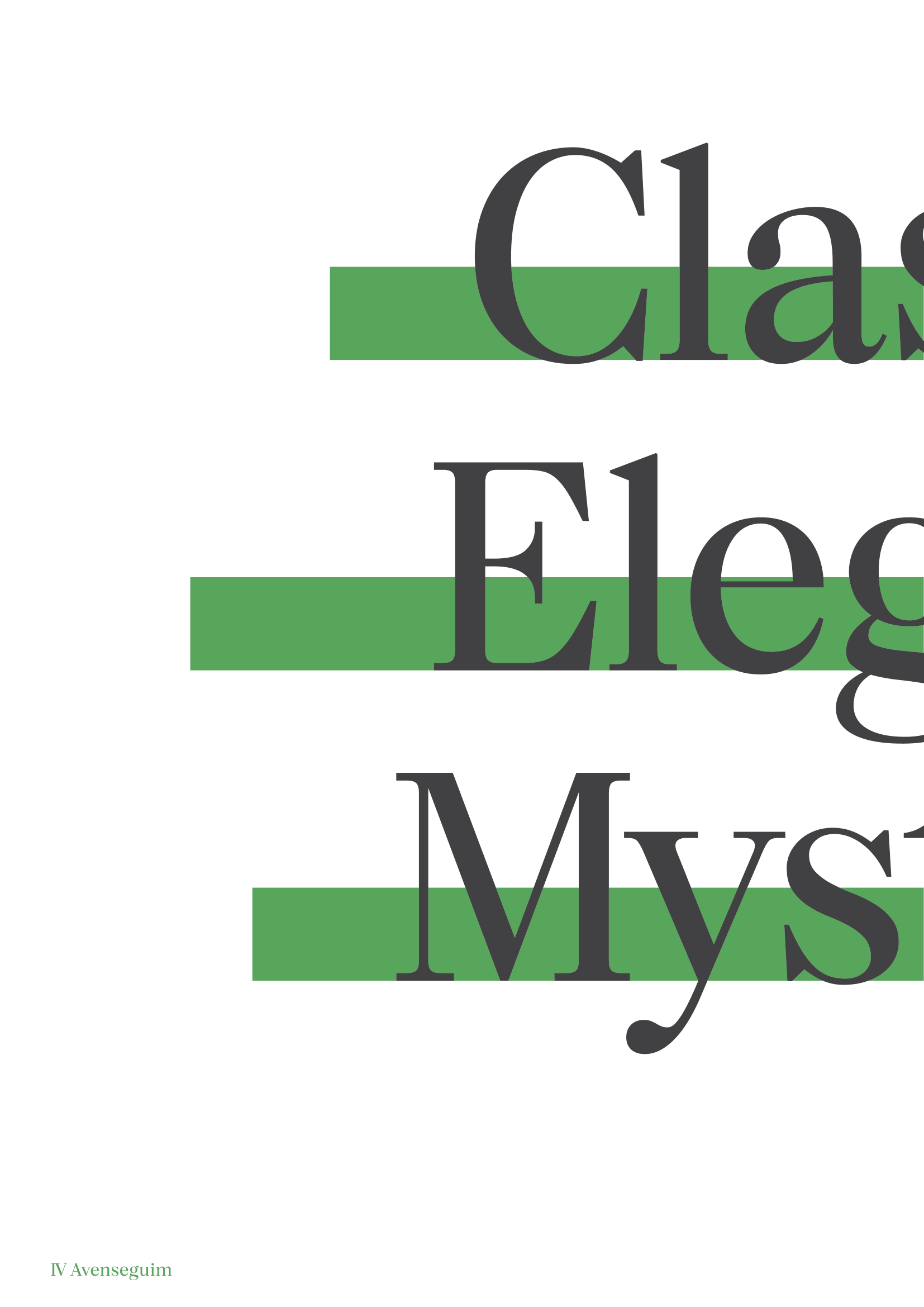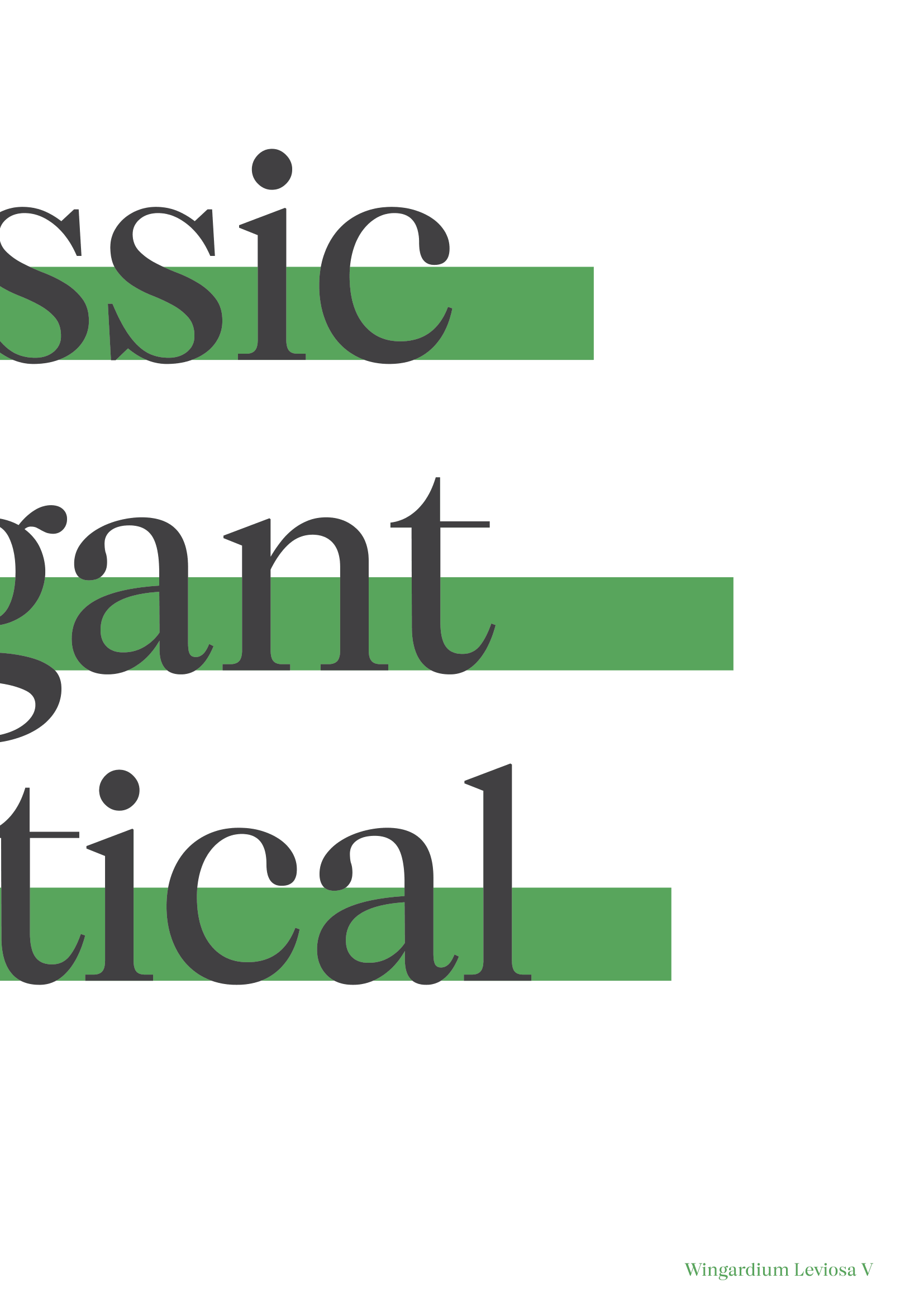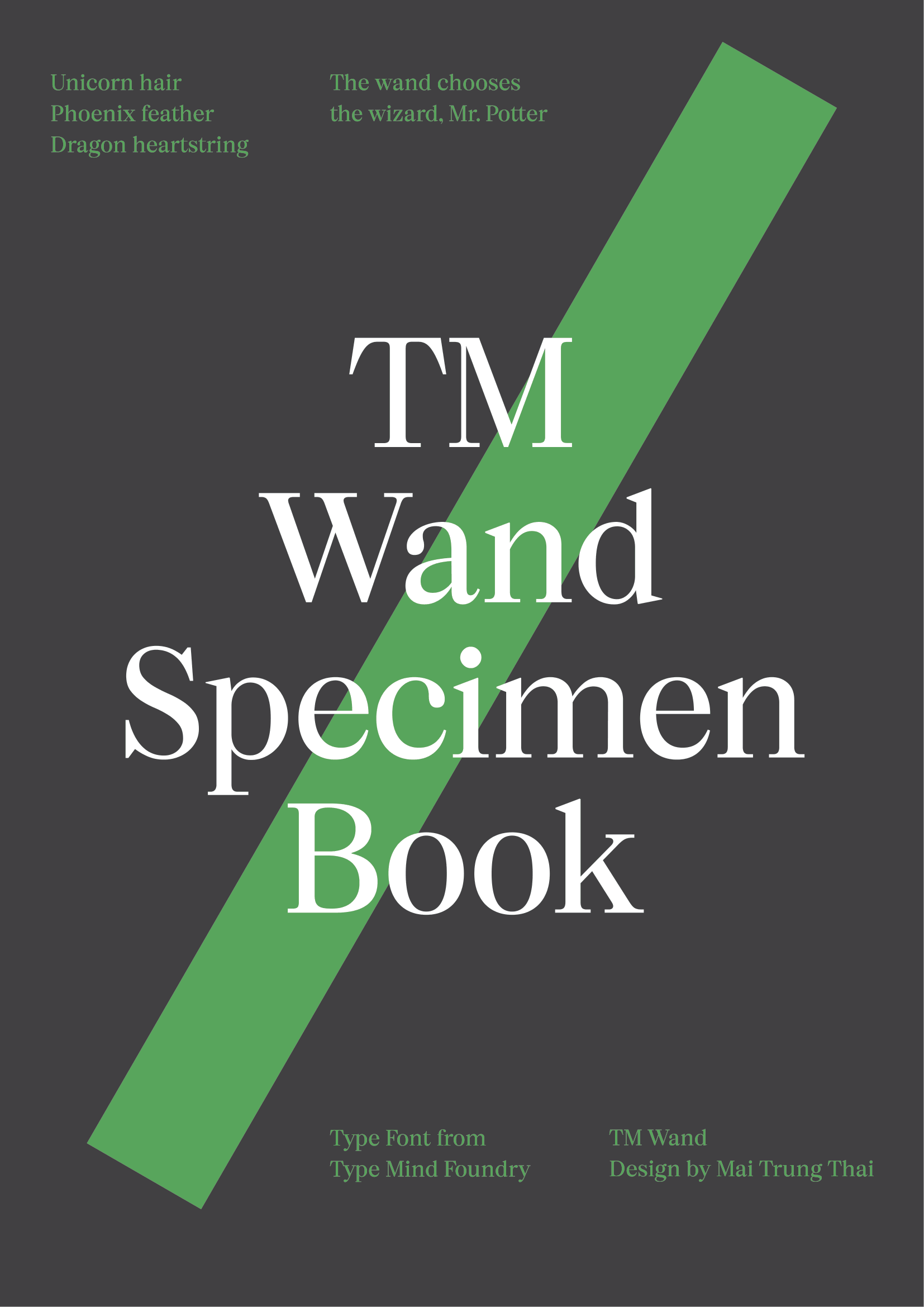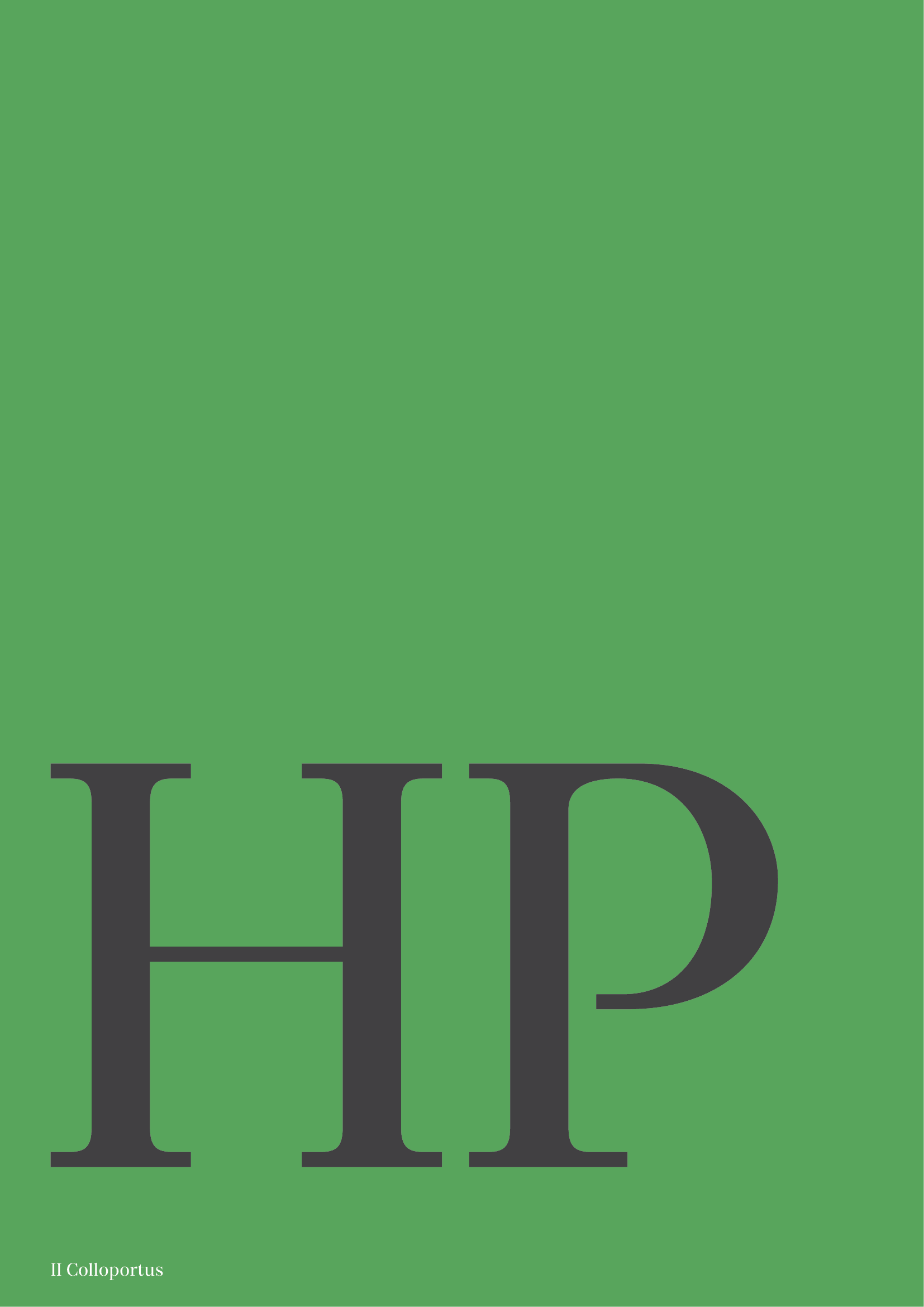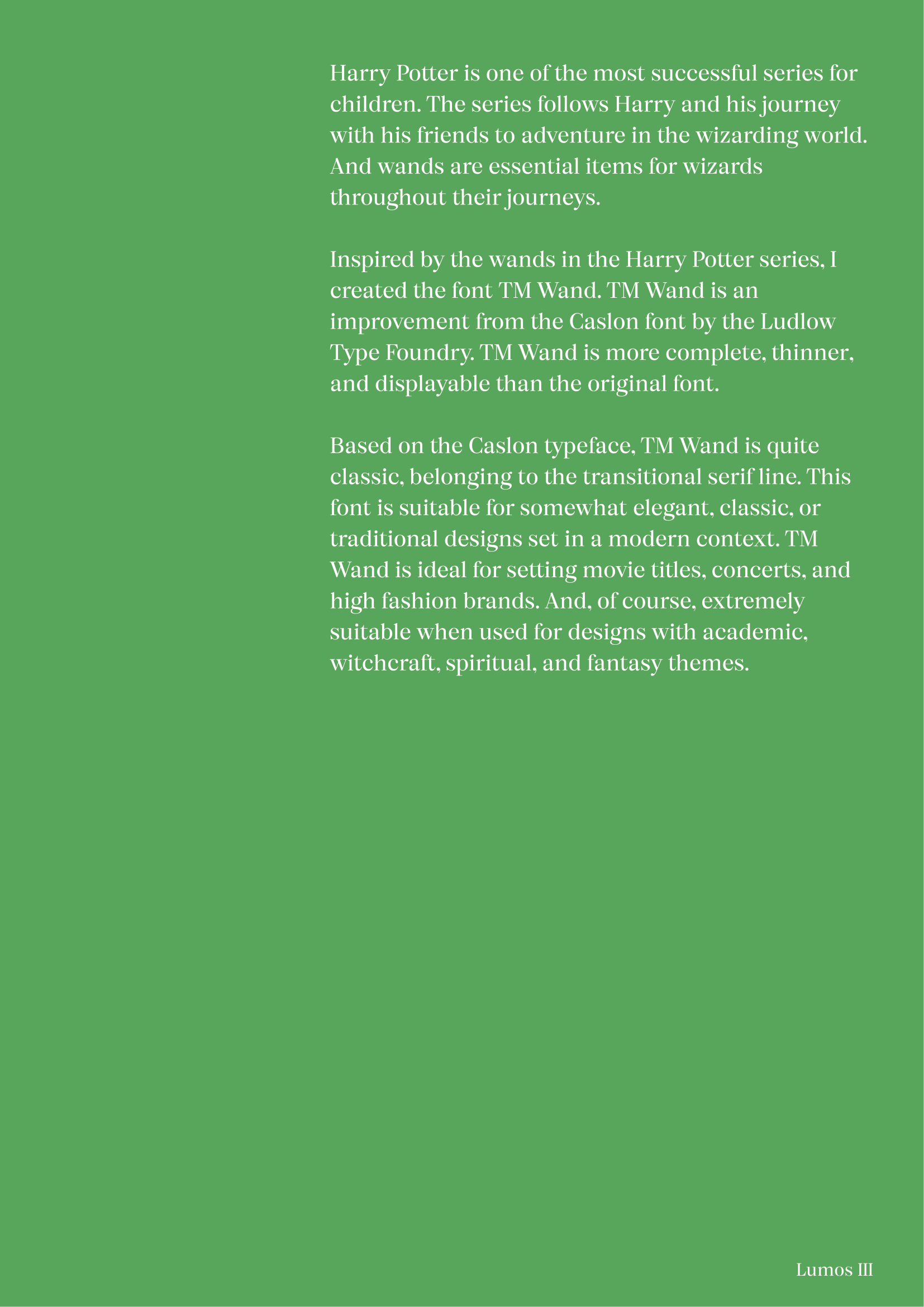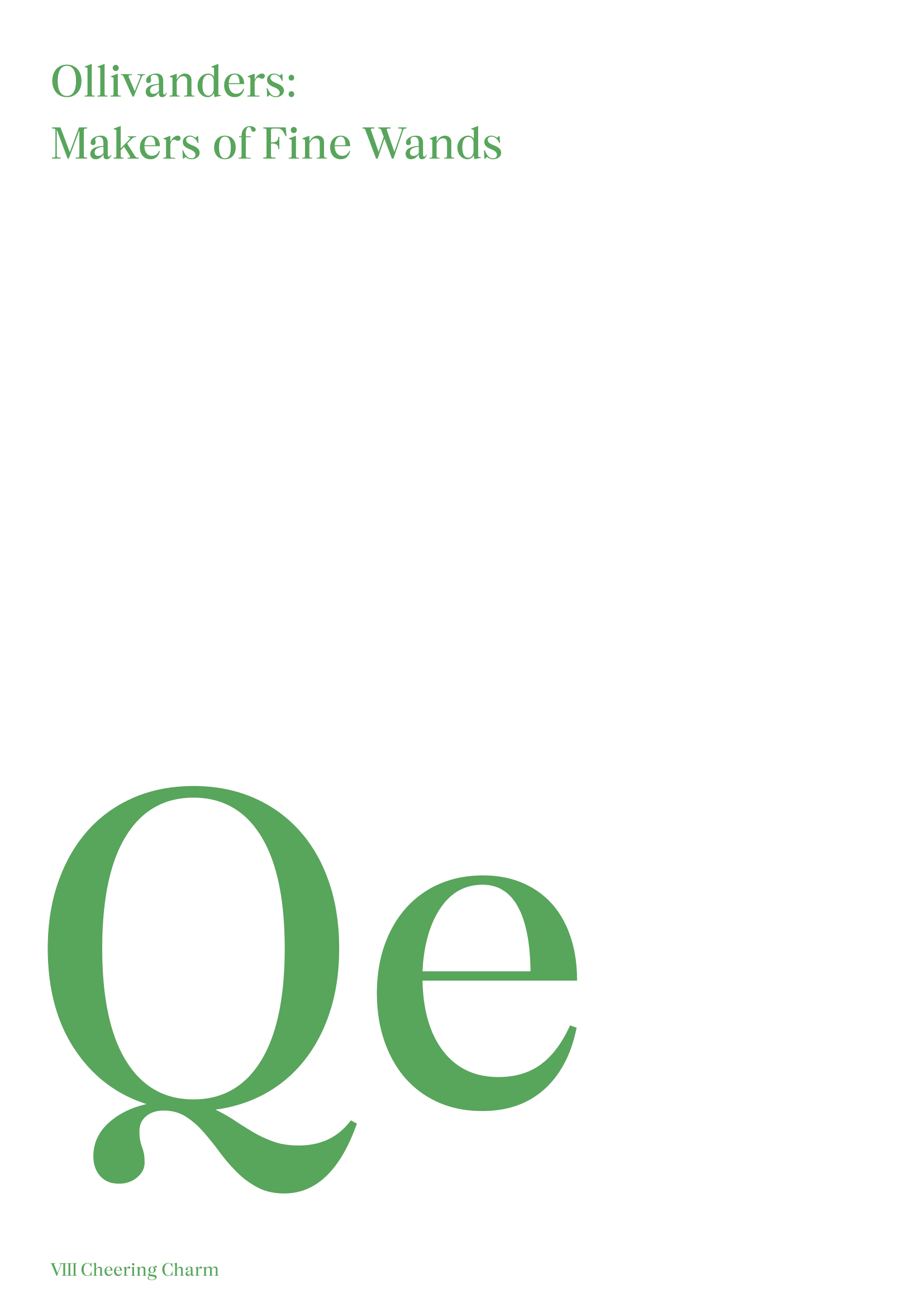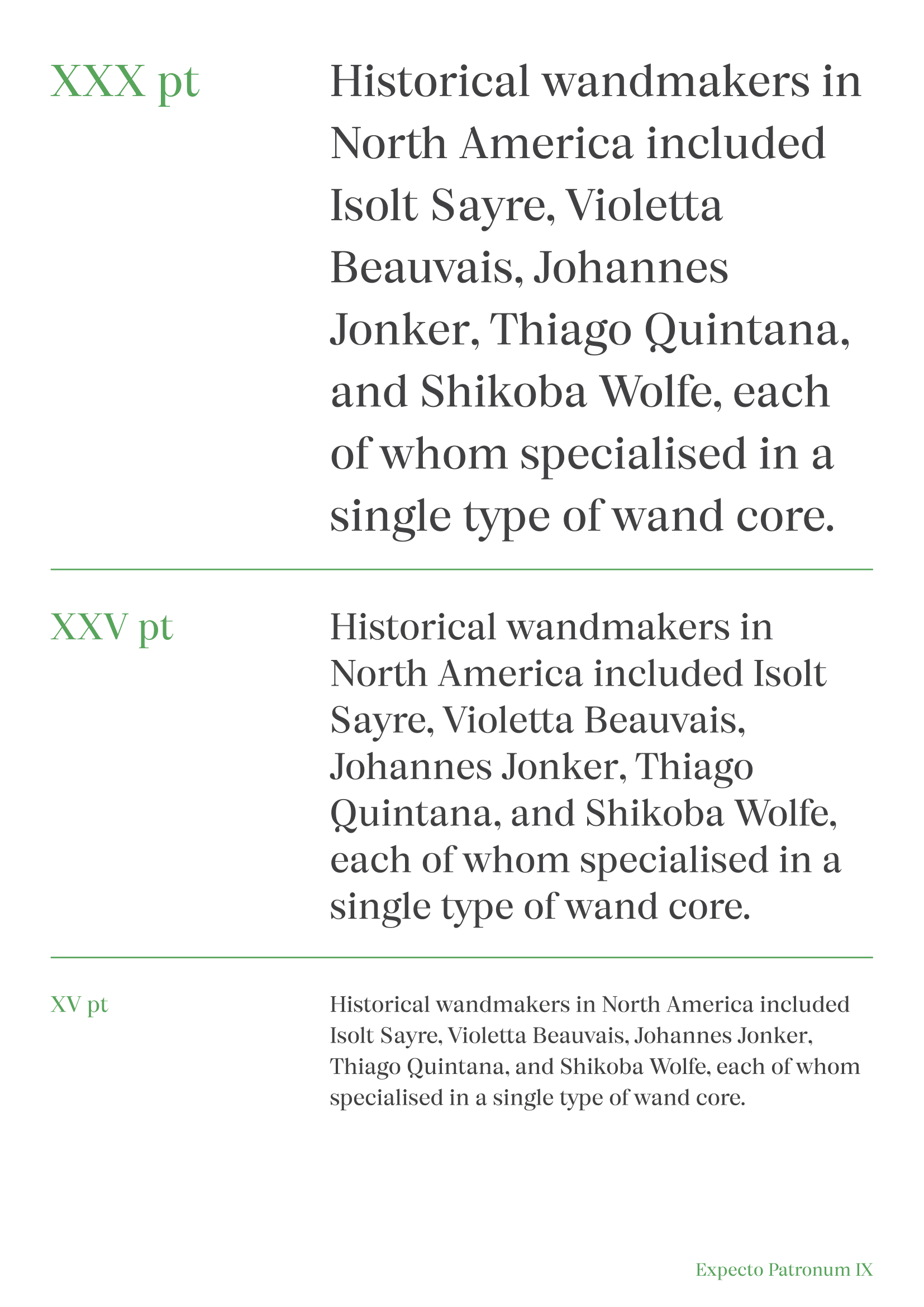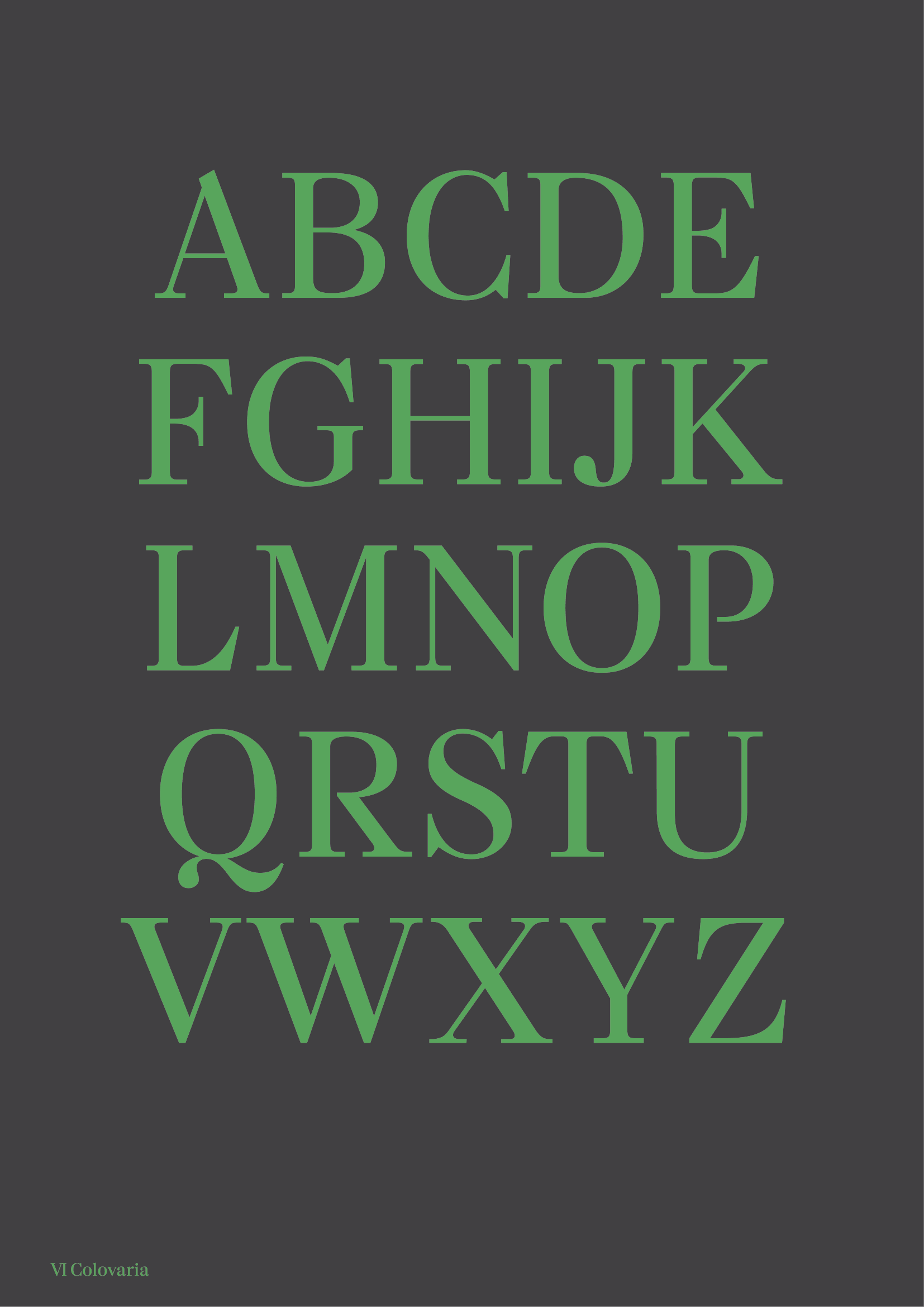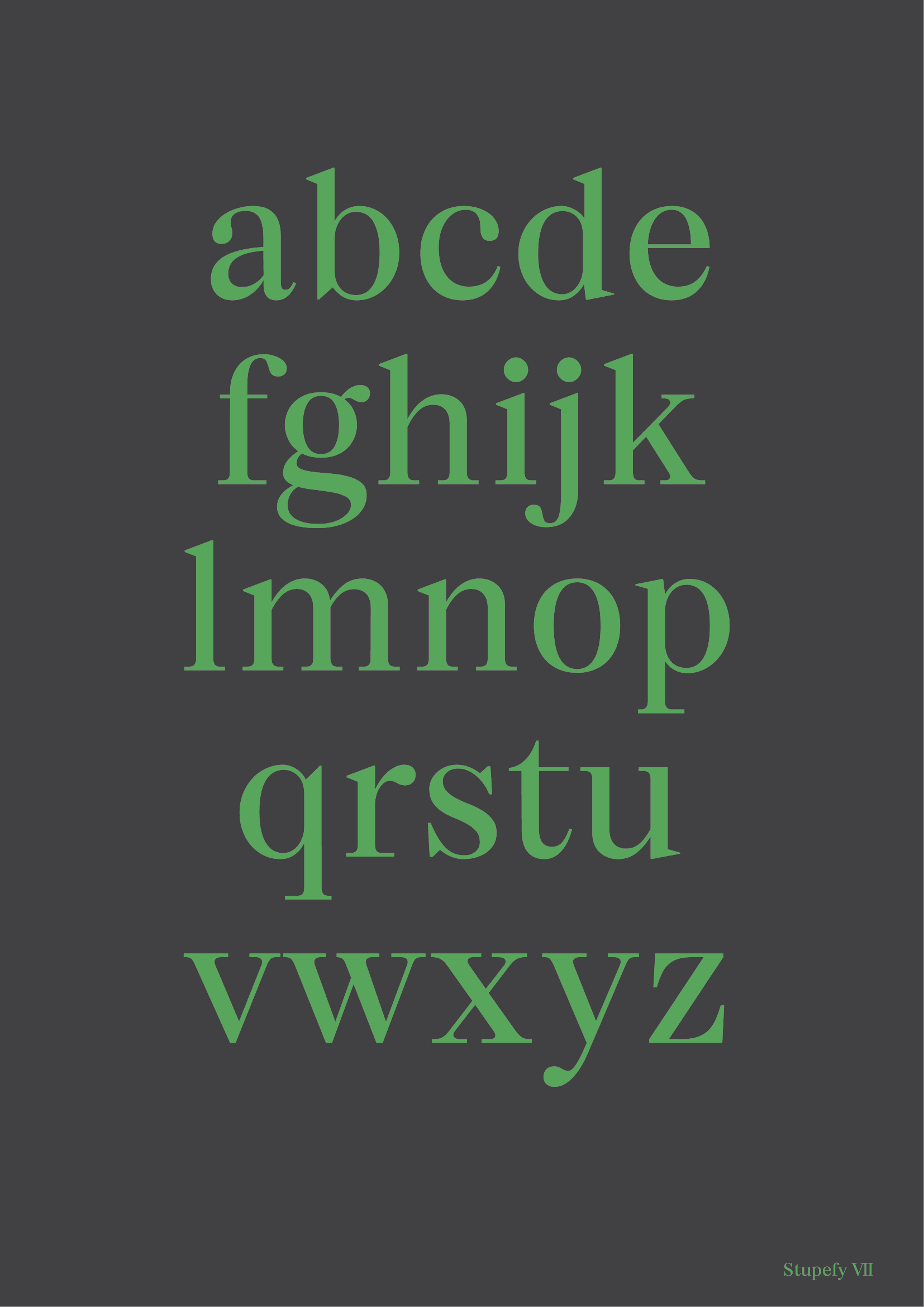
TM Wand
Về TM Wand: Bắt đầu với Ludlow Caslon của Ludlow Typograph Company, TM Wand lựa chọn weight Regular để phục dựng. TM Wand cầu toàn đi các nét vòm tròn trịa, xử lý tương phản nét vừa phải nên đem lại một tinh thần mới cho bản gốc, phù hợp cho cả tiêu đề lớn và các đoạn mô tả cỡ vừa.
Transitional Serif
Display
Mai Trung Thái